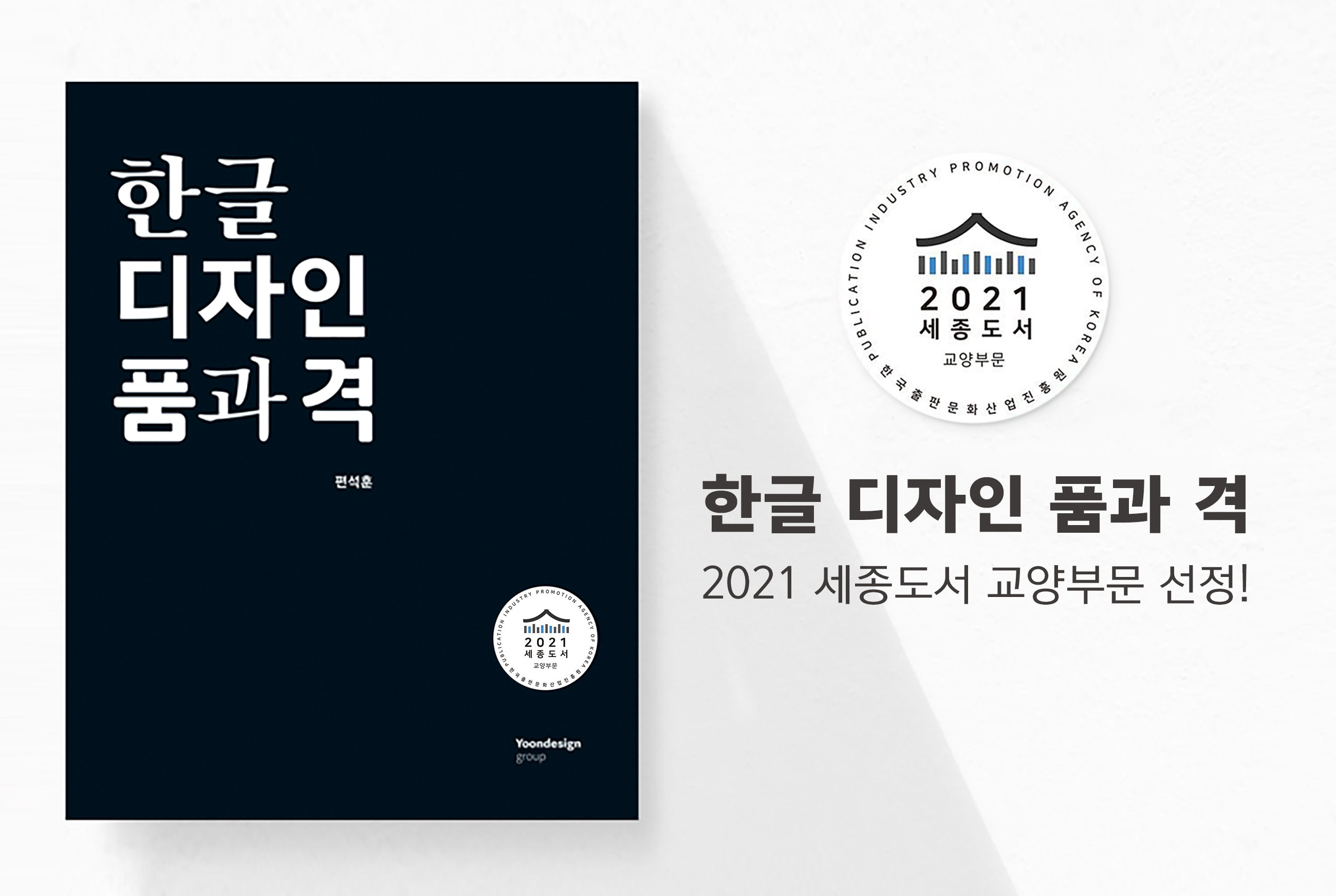
2021 세종도서 교양부문에 선정된 ㈜윤디자인그룹 편석훈 대표의 저서 '한글 디자인 품과 격'
㈜윤디자인그룹은 한글디자인 서적 ‘한글 디자인 품과 격’이 2021년도 세종도서 교양부문에 선정됐다고 20일 밝혔다. 이를 통해 ㈜윤디자인그룹은 한글디자인 철학의 깊이를 다시 한번 인정받았다.
세종도서는 문화체육관광부와 한글출판문화산업진흥원에서 우수출판콘텐츠 제작 활성화 및 책 읽는 문화 확산을 위해 매년 학술부문과 교양부문의 도서를 선정, 전국 공공도서관, 전문 도서관, 초·중·고등학교 등 90여 곳에 보급하는 문화 콘텐츠 사업이다.
한글 디자인 품과 격은 윤디자인그룹의 CEO이자 크리에이티브 디렉터인 편석훈 대표가 저술한 한글디자인 서적으로, 윤디자인그룹의 30년 한글 타이포그라피 역사를 정리하고 전용서체를 기반으로 한 타이포브랜딩의 영역의 실제 경험을 소개한 책이다. 장장 7년에 걸친 ‘대한민국독립만세체’ 제작기, <월인석보>, <간이벽온방>과 같은 고문서 속 옛 글자를 디지털 폰트로 복원한 과정, 1994년 완성 이래 무려 30년 가까운 시간 동안 시리즈를 이어 오고 있는 ‘윤명조’ 및 ‘윤고딕’ 이야기 등을 소개했다. 또한 지방자치단체 전용서체 개발 당시의 에피소드, 기업 전용 서체 프로젝트 진행시 실무자들과의 긴장감 넘치는 진행과정 등 그동안 총괄해 온 후일담들도 생생하게 담았다.
㈜윤디자인그룹, '한글 디자인 품과 격' 2021년도 세종도서 교양부문 선정
2021 세종도서 교양부문에 선정된 ㈜윤디자인그룹 편석훈 대표의 저서 '한글 디자인 품과 격'
㈜윤디자인그룹은 한글디자인 서적 ‘한글 디자인 품과 격’이 2021년도 세종도서 교양부문에 선정됐다고 20일 밝혔다. 이를 통해 ㈜윤디자인그룹은 한글디자인 철학의 깊이를 다시 한번 인정받았다.
세종도서는 문화체육관광부와 한글출판문화산업진흥원에서 우수출판콘텐츠 제작 활성화 및 책 읽는 문화 확산을 위해 매년 학술부문과 교양부문의 도서를 선정, 전국 공공도서관, 전문 도서관, 초·중·고등학교 등 90여 곳에 보급하는 문화 콘텐츠 사업이다.
한글 디자인 품과 격은 윤디자인그룹의 CEO이자 크리에이티브 디렉터인 편석훈 대표가 저술한 한글디자인 서적으로, 윤디자인그룹의 30년 한글 타이포그라피 역사를 정리하고 전용서체를 기반으로 한 타이포브랜딩의 영역의 실제 경험을 소개한 책이다. 장장 7년에 걸친 ‘대한민국독립만세체’ 제작기, <월인석보>, <간이벽온방>과 같은 고문서 속 옛 글자를 디지털 폰트로 복원한 과정, 1994년 완성 이래 무려 30년 가까운 시간 동안 시리즈를 이어 오고 있는 ‘윤명조’ 및 ‘윤고딕’ 이야기 등을 소개했다. 또한 지방자치단체 전용서체 개발 당시의 에피소드, 기업 전용 서체 프로젝트 진행시 실무자들과의 긴장감 넘치는 진행과정 등 그동안 총괄해 온 후일담들도 생생하게 담았다.